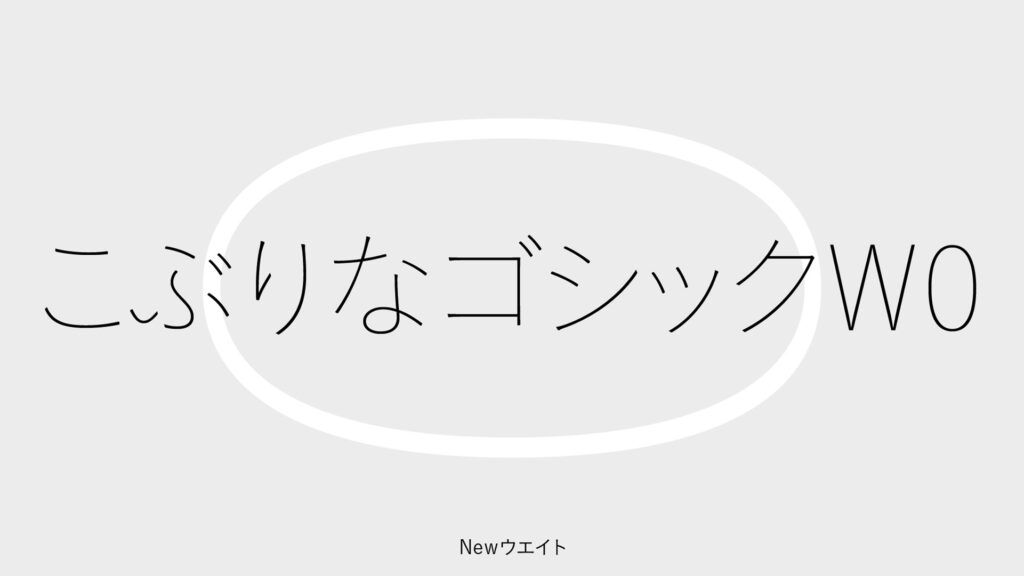
SCREEN GA ヒラギノフォントの新書体「こぶりなゴシック W0」を2月14日より販売開始、優しく軽やかな人気書体の最も細いモデル
株式会社SCREENグラフィックソリューションズは2月14日、ヒラギノフォントの新書体「こぶりなゴシック W0」を販売開始する。
「こぶりなゴシック」は2006年に販売を開始したフォントで、「字面が小さめで、ふつうで素直なかたちを持ち、詰め組みしたときも美しい、やわらかな印象の書体」をコンセプトに開発された。縦組みでも横組みでもバランス良く組め、ベタ組みでも美しいことから、エディトリアルデザインを中心に高い評価を獲得。今なお根強い人気を誇っている。
2006年のリリース当初はW1/W3/W6をラインアップ、2021年に最も太いウエイトとなる「こぶりなゴシック W9」を追加。そしてこのほど、最も細いウエイトの「こぶりなゴシック W0」を新たにラインアップに加えた。